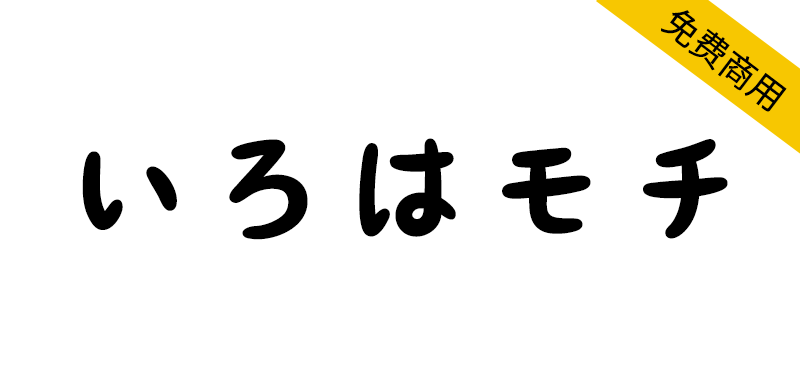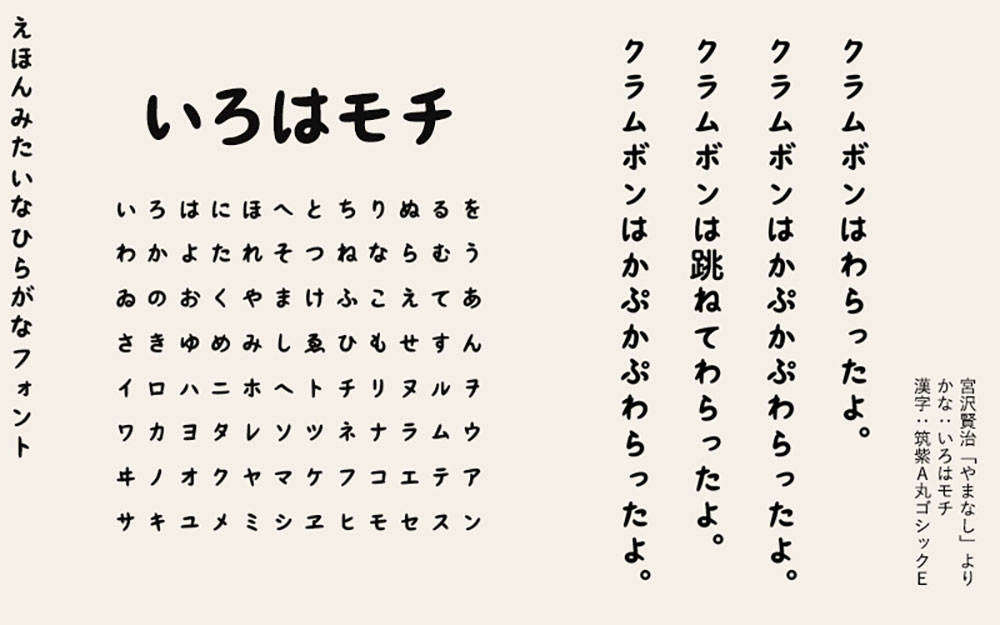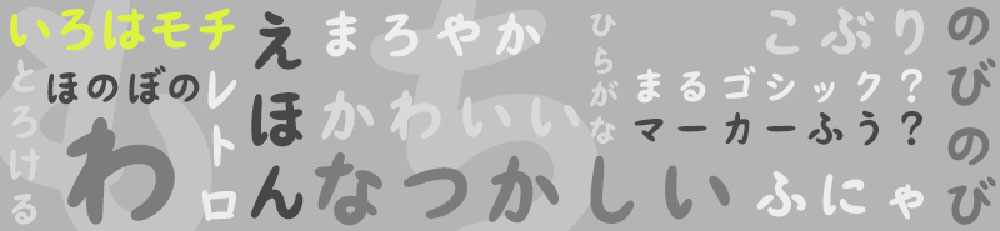
いろはモチ是一款适合图画书的怀旧平假名字体。骨架是以“いろはマル”为原型的,所以有些老套。这是仅适用于平假名和片假名的字体。此外,还包括一些基本的标点符号(标点符号、括号等符号)。
絵本に合いそうな懐かしい感じのひらがなフォントです。骨格は『いろはマル』をベースにしたのでなんとなくオールド寄り。ひらがな・カタカナのみのフォントです。おまけでいくつか基本的な約物(句読点や括弧などの記号)も入っています。